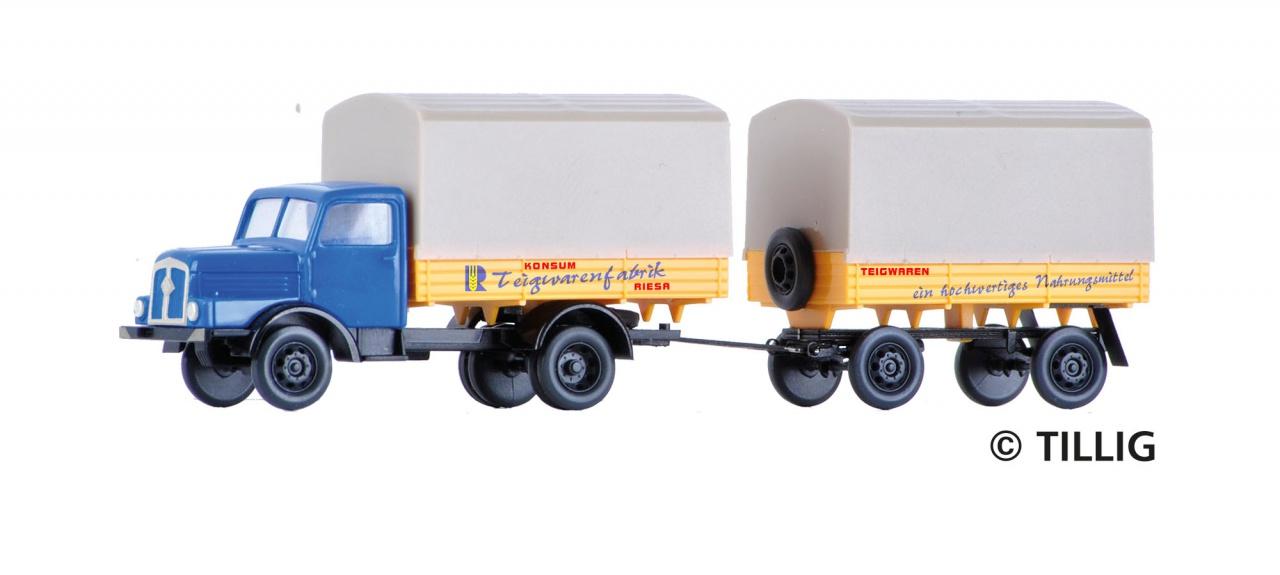
Schreibschrift für Fahrzeug der Nudelwerke Riesa gesucht
für eine Modellbeschriftung suche ich den Schriftzug für Fahrzeuge H3A der Nudelwerke Riesa. Es geht um die Schrift für Konsum/Riesa sowie die Schreibschrift für Teigwarenfabrik. Gibt es Fonts für mein Anliegen und wo kann ich sie erwerben?
Zum Einen ist das Foto leider etwas zu klein für meine müden Augen, zum Anderen wird es sich eh um das Werk eines Schildermalers handeln, das man exakt so nicht als Font finden wird. Ich kann also nur raten, wenn ich für die Schreibschrift zur  Rage Italic oder Mojito tendiere. »Konsum« und »Riesa« kann ich leider gar nicht richtig erkennen, um irgendeine Empfehlung abzugeben …
Mich stört bei vielen Schriften das runde r, das zu amerikanisch wirkt …
Deutsche Werbe-Schreibschriften haben ja in der Regel das normale Antiqua-r.
erst einmal herzlichen Dank für Eure Mithilfe. Ich habe hier noch ein Foto eines Modells gefunden , wo ich vermute, dass hier eine ganz "normale" Schrift  angewendet wurde?